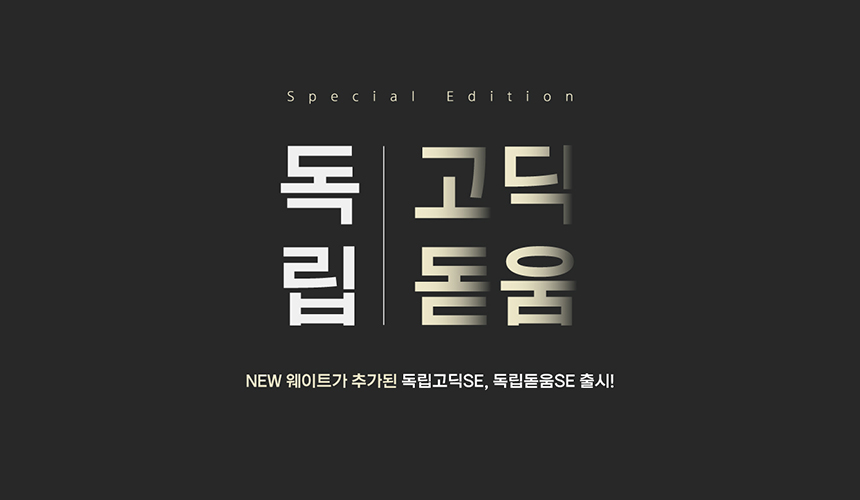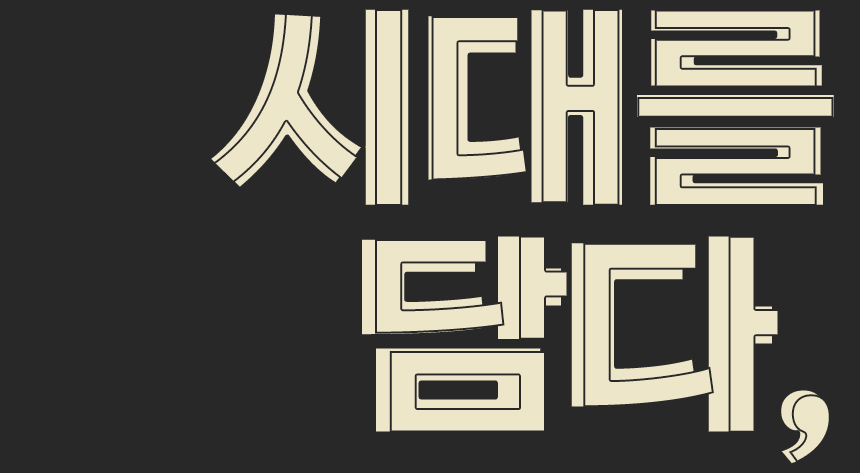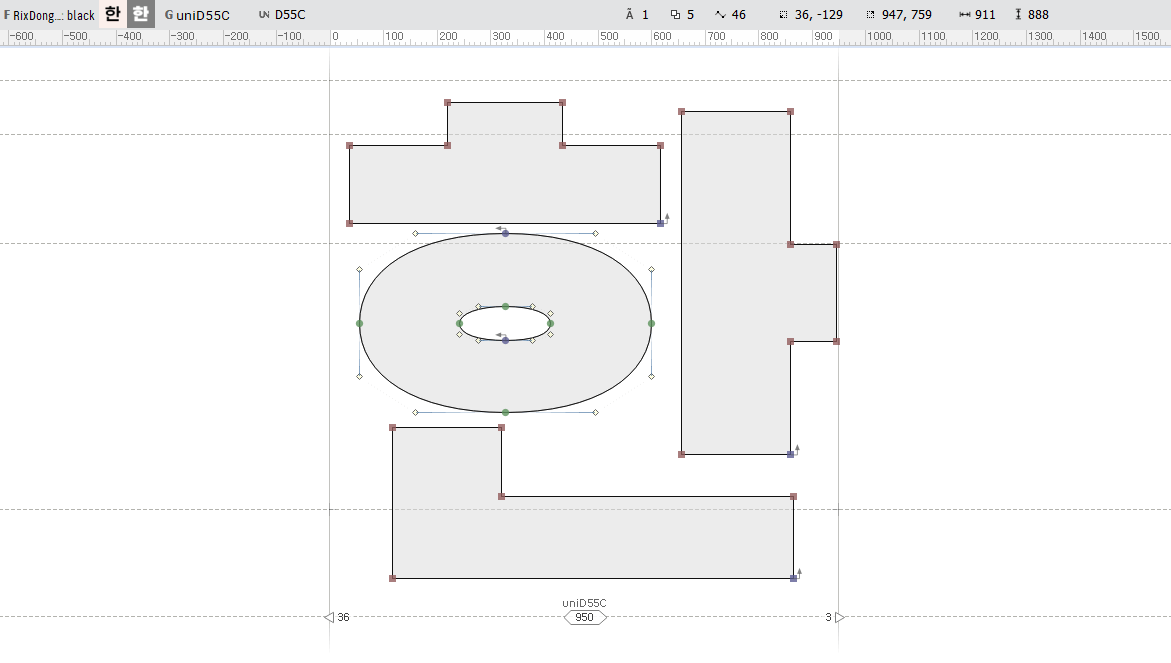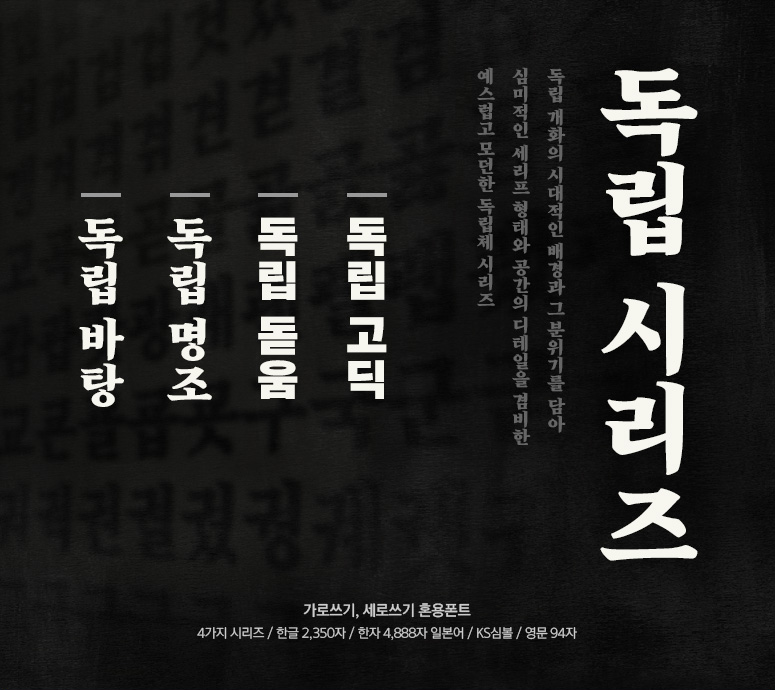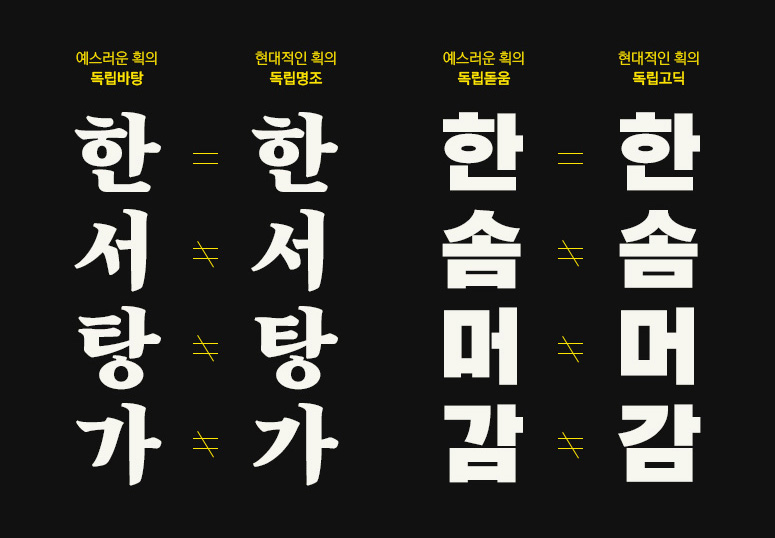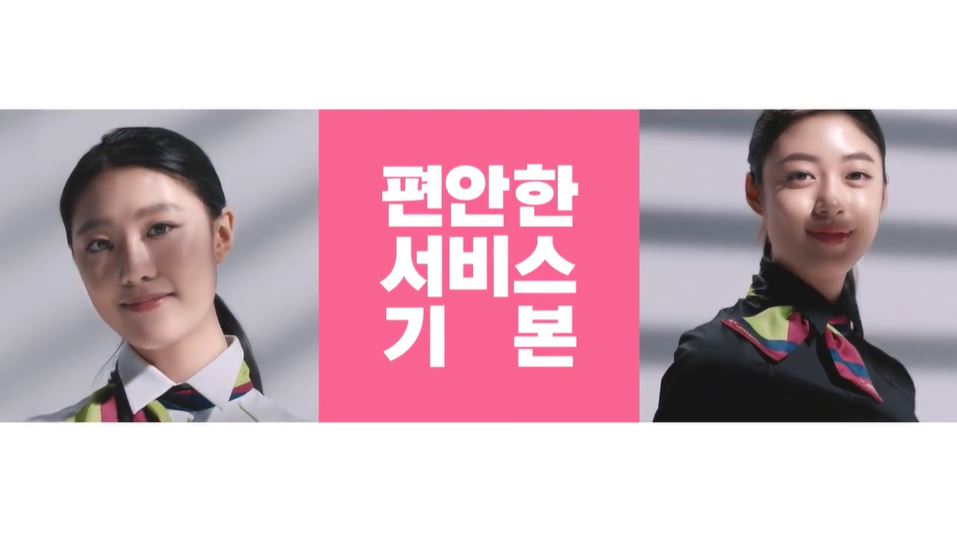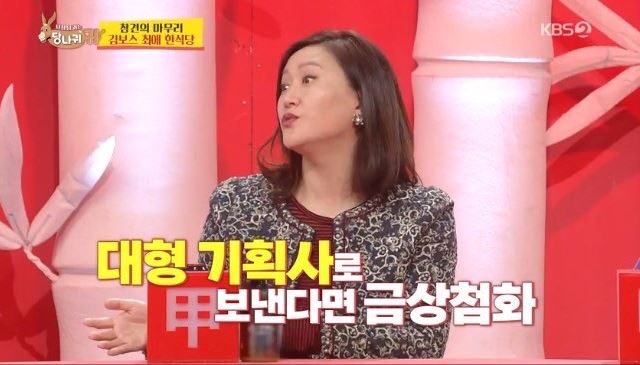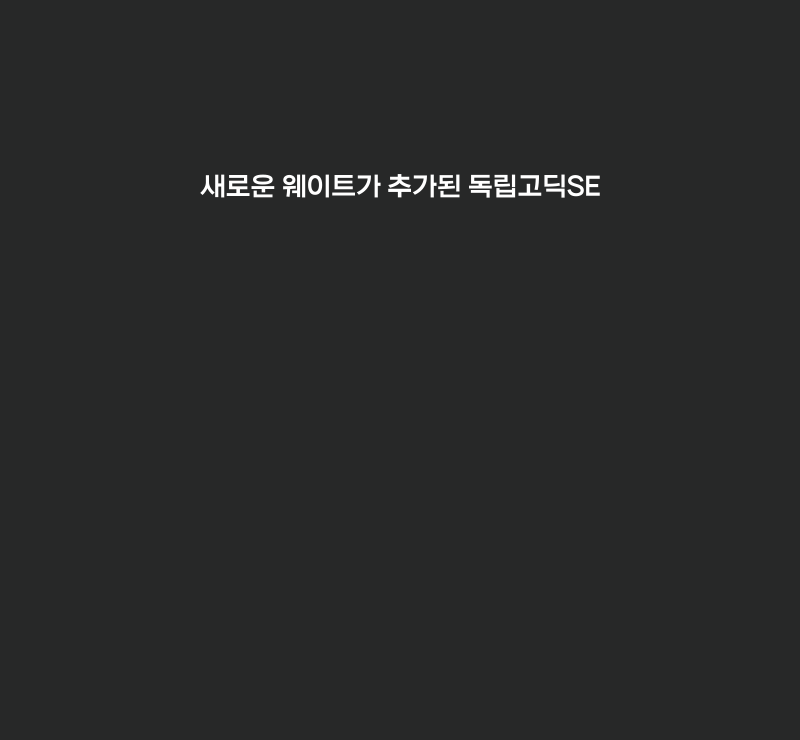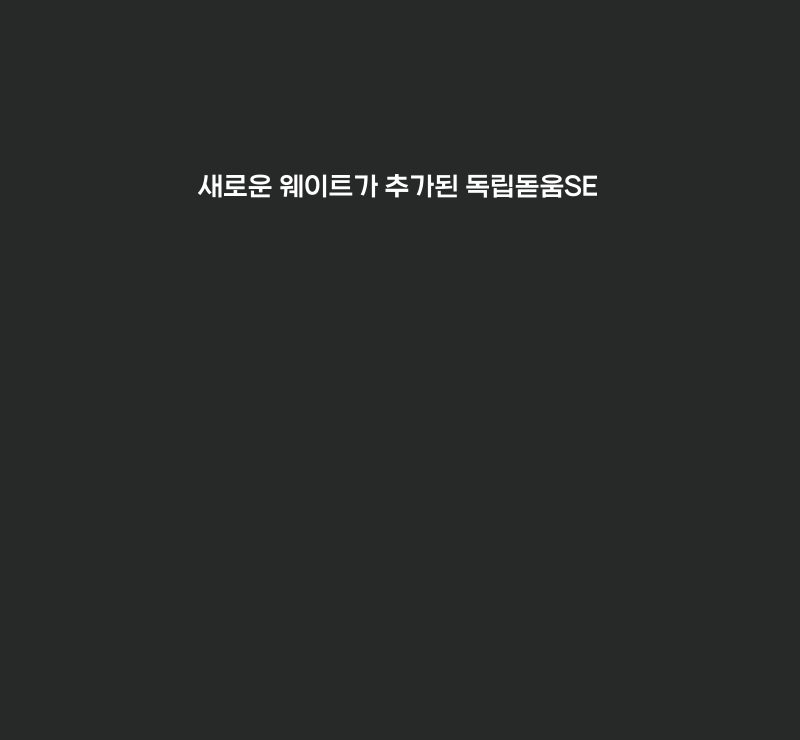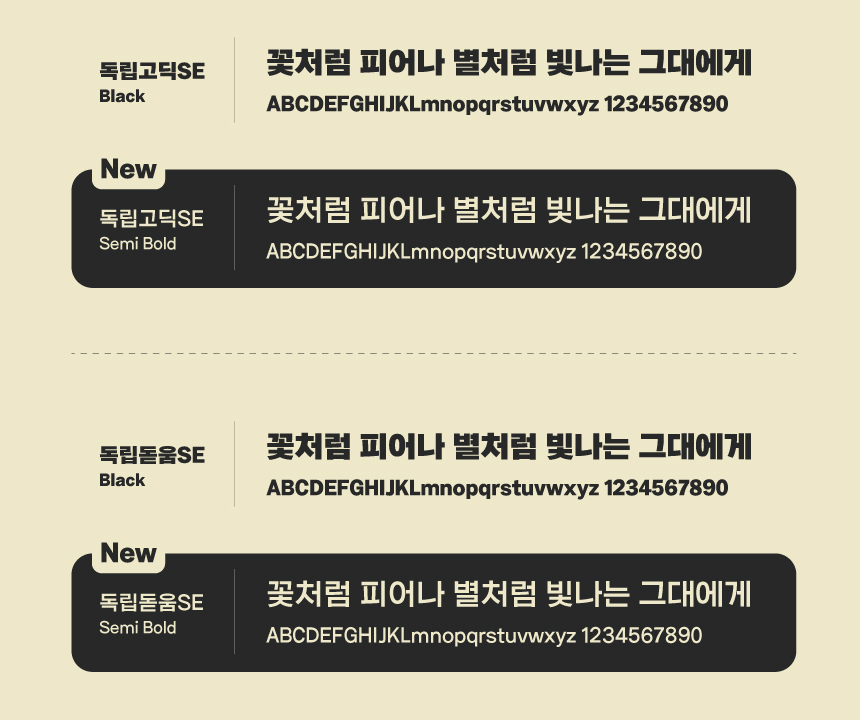
안녕하세요. 3월의 신서체는 기존 독립시리즈의 고딕과 돋움체를 업그레이드한 「Rix독립고딕SE」, 「Rix독립돋움SE」입니다. 독립시리즈는 독립고딕, 돋움 외에도 독립명조와 독립바탕까지 총 4가지 패밀리를 가진 서체 시리즈로 2018년도에 처음 세상에 나왔습니다. 그동안 많은 사랑을 받은 서체인 만큼 활용도를 높이기 위해 이번에 폰트 업그레이드를 진행했는데요. 작업을 맡아주신 박지영 디자이너를 만나봤습니다🎤
안녕하세요, 박지영 디자이너님. 인터뷰로 처음 인사드리게 되었는데 소개 한번 부탁드릴게요!
안녕하세요. 독립고딕과 독립돋움 Special Edition으로 처음 인사드리게 된 새싹 디자이너 박지영이라고 합니다.
3월의 신서체를 맡아주셨는데, 어떻게 기획하게 되신 폰트인가요?
독립고딕과 독립돋움은 두꺼운 획이 큰 특징이고, 강하고 센 어조나 헤드라인에 잘 어울리는 서체라고 생각합니다. ‘이런 독립의 쓰임이 더 다양했으면 좋겠다’가 기획 의도였습니다. SE에서 새로 파생된 세미볼드(Semi Bold) 웨이트는 기존 독립 서체인 Black보다 공간감의 비례가 좀 더 넓게 제작되었기 때문에 예스러운 느낌이 강조되었다고 볼 수 있습니다.
아무래도 기존의 스테디셀링 폰트를 업그레이드하는 것이 쉽지는 않았을 것 같아요. SE 버전에서 어떤 부분을 가장 신경 썼는지 또는 가장 어려웠는지?
블랙 정도의 두께를 얇게 파생해야 하다 보니 획을 처음부터 다시 그리게 되는 상황이었어요. 모든 게 처음인 저에겐 글자가 얼만큼의 짜임새를 지녀야 기존의 독립과 비슷해 보일 수 있을지, 획의 두께는 어떻게 설정해야 하는지(회색도) 등 모듈을 재정의 해야 한다는 점이 가장 어려웠어요. 그래도 기존 독립을 참고하며 제작한다는 게 큰 위안이었고, 또 많이 성장할 수 있는 기회가 되어 이 작업을 맡아서 할 수 있었던 것에 감사함을 느끼고 있습니다.
사실 독립고딕과 독립돋움의 생김새가 굉장히 비슷해 보이는데, 어떤 차이점이 있나요?
독립고딕과 독립돋움은 같은 뼈대를 사용하지만 자소 형태에서 차이를 보입니다. 독립고딕 같은 경우엔 ㅅ, ㅈ, ㅊ 꼴에서 대칭형 자소의 모습을 보이며, 표현을 절제한 고딕의 중립적인 성격을 지킵니다. 반면 독립돋움 같은 경우엔 ㅅ, ㅈ, ㅊ, ㅁ, ㅂ 등의 자소에서 손글씨의 획이 반영되었습니다. 같은 골격을 사용하더라도 그 안에서 고딕은 모던한 인상을, 돋움은 더 예스럽고 친근한 인상을 느낄 수 있습니다.
단기로는 추후에 출시 될 폰트가 예정되어 있어 그것을 완성하는 것이 목표이고요. 장기로는 강하고 선명한 인상의 독립고딕과 독립돋움을 파생해봤으니, 반대로 유려한 곡선을 사용하는 하늘하늘한 인상의 글자를 그려보고 싶습니다. 지금까지 읽어주셔서 고맙습니다.
시대를 담은 독립시리즈
새롭게 업그레이드 된 독립고딕과 독립돋움의 서체 패밀리 독립시리즈는 개화기의 시대적 분위기를 담아 강하고 무거운 느낌의 형태로 기획되었습니다. 예스러움과 모던함이 공존하도록 세리프가 있는 서체와 고딕형의 서체를 개발했고 심미적인 형태와 비율을 고려하여 제작되었습니다.
크게 예스러운 획과 현대적인 획으로 나뉘는 독립시리즈는 서로 같은 모듈과 형태 등을 사용하지만 각각 다른 골격을 사용하여 전혀 다른 인상과 분위기를 만들어내는 특징이 있습니다.
새로운 웨이트 Special Edition
꽉 찬 골격의 단단하고 강한 획의 느낌은 그대로 살리고, 최적의 비율로 획의 두께를 설정했습니다. 독립고딕SE는 두껍고 단단한 획, 절제된 표현과 간결한 직선의 형태에서 모던함이 돋보이고, 독립돋움SE는 손글씨의 획을 적용한 자소 디자인으로 좀 더 예스러운 느낌이 강조되었습니다.
두 서체 모두 두껍고 무거운 인상이 강했다면, SE 버전은 보다 높은 활용도와 사용성을 고려하여 제작되었다고 볼 수 있습니다. 추가 파생한 Semi Bold 웨이트로 더 다양한 활용이 가능합니다.
독립고딕SE, 독립돋움SE는 같은 950의 넓은 글자 너비로 정사각 꽉 찬 모듈로 설계되었으며, 가로 세로 거의 동일한 획 굵기로 제작했습니다. 획의 굵기는 서체에 적합한 공간 비율에 맞게 조절했습니다.
글자의 획이 얇아지면서 속공간이 넓어지므로 전체적으로 한층 시원한 인상을 느낄 수 있습니다. 넓어진 공간 비율로 편안하면서도 힘 있고 좀 더 복고적인 이미지를 줄 수 있습니다.
이렇게 활용해 보세요
독립시리즈는 영문, 숫자, 한자, 일본어까지 한글과 통일된 디자인을 적용하여 이질감 없이 국문과 혼용하여 사용할 수 있습니다. 높은 가독성으로 단문이나 장문 모두 잘 읽힙니다.
실제로 독립 서체들은 인쇄물이나 영상 자막 등에서 활용도가 높은데요. 힘 있고 단단한 골격이 눈길을 끌어 효율적으로 사용할 수 있습니다. 주목성이 필요한 콘텐츠에 활용해 보세요!
3월은 대한민국의 독립 의사를 세계만방에 알린 뜻깊은 날을 기념하는 삼일절이 있습니다. 독립을 염원하며 그 시대를 살아낸 강하고 굳은 마음들을 생각하면서 지금 우리가 사는 시대에 대해 감사한 마음을 가질 수 있는 달이었으면 좋겠습니다. 따스함이 서서히 스며드는 3월에 새로워진 독립시리즈 SE 서체와 만나보세요! 감사합니다.